Чем отличаются шрифты без засечек для текста и крупных надписей
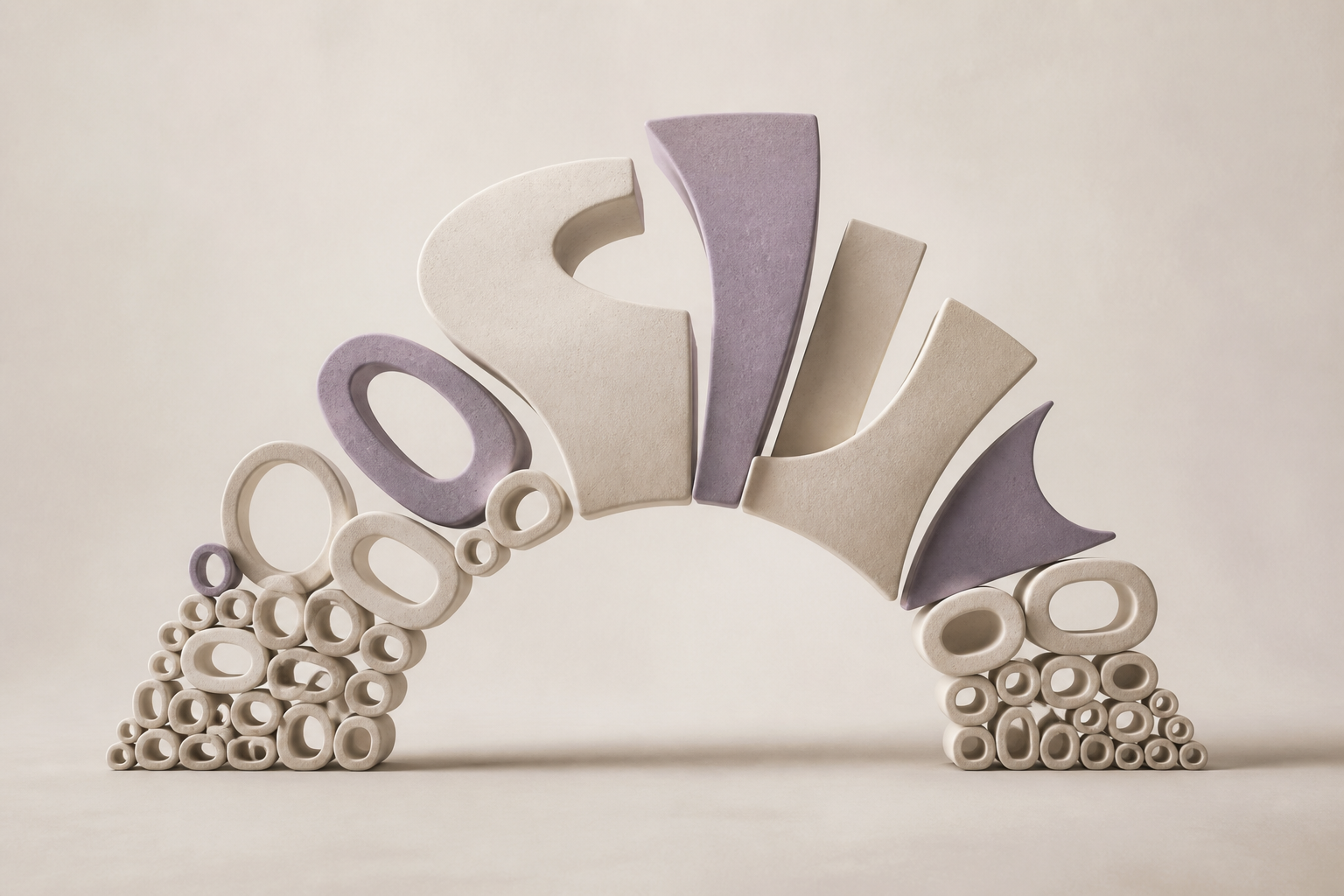
Чем отличаются шрифты без засечек для текста и крупных надписей
Шрифты без засечек для текста и крупных надписей решают разные задачи: первые сохраняют читаемость в длинных строках и при небольшом кегле, вторые создают выразительный образ в заголовке или плакате. Разница заключается в пропорциях, деталях знаков, интервалах и поведении при масштабировании. Ниже разберём, как выбрать подходящий гротеск, настроить набор и избежать ошибок.
Почему один гротеск не одинаково работает везде
Шрифт без засечек, или гротеск, не является универсальным инструментом только потому, что у его букв нет небольших завершающих штрихов. В тексте шрифт должен помогать быстро распознавать слова, удерживать ритм строки и не утомлять взгляд. В крупной надписи он может вести себя смелее: менять ширину знаков, усиливать контраст толщин, использовать необычные формы и заметный характер.
На выбор влияет не только внешний вид букв, но и условия чтения. Статья обычно состоит из множества строк, поэтому важны открытые внутренние просветы, умеренная плотность, различимость похожих знаков и предсказуемые интервалы. Заголовок на обложке читается иначе: у него меньше слов, больше визуального пространства и выше роль силуэта, композиции и эмоционального тона.
Особенности текстового шрифта без засечек
Текстовый гротеск проектируют с расчётом на устойчивое чтение в абзацах, интерфейсах, подписях и навигации. Его буквы обычно имеют хорошо различимые формы, достаточно открытые апертуры и спокойный рисунок. Даже при плотном наборе символы не должны сливаться в серую полосу. Важна и высота строчных знаков: достаточно крупная x-высота помогает сохранить разборчивость, но чрезмерно большая делает текст визуально тяжёлым.
У текстового sans serif часто более нейтральный характер. Это не означает полное отсутствие индивидуальности: различия проявляются в форме кавычек, цифр, знаков препинания, букв а, е, g, в ширине знаков и завершениях штрихов. Однако такие особенности подчинены общей задаче — не отвлекать внимание от содержания. Поэтому хороший текстовый шрифт может казаться незаметным, хотя именно эта незаметность поддерживает комфорт чтения.
На какие признаки смотреть в текстовом гротеске
- Проверяйте различимость похожих букв, например и, й, п, т, ш и щ в кириллице.
- Оценивайте размер внутренних просветов в буквах о, е, с, в и а.
- Смотрите, не становятся ли круглые знаки слишком тесными в длинной строке.
- Проверяйте цифры, скобки, кавычки, тире и другие знаки, а не только алфавит.
- Учитывайте наличие кириллицы, нужных языков, валютных символов и математических знаков.
- Тестируйте обычное, полужирное и курсивное начертания в одном документе.
Что такое дисплейный шрифт для крупных надписей
Дисплейный шрифт предназначен для крупного размера, когда зритель сначала воспринимает общую форму слова, а затем читает отдельные знаки. Он может быть узким, широким, геометричным, мягким, угловатым или контрастным. В заголовке допустимы детали, которые в маленьком кегле исчезли бы или ухудшили бы чтение: необычные терминалы, декоративные соединения, нестандартные пропорции и более заметный ритм.
У дисплейного sans serif сильнее выражен голос бренда или проекта. Крупная надпись на постере должна не только сообщать слова, но и задавать настроение. Геометрический гротеск может выглядеть технологично и строго, гуманистический — дружелюбно, узкий — динамично и экономно расходовать ширину, а тяжёлое начертание — создавать ощущение силы. Эти характеристики работают именно благодаря масштабу и свободному пространству вокруг текста.
Что меняется при увеличении кегля
При крупном размере становятся заметны неровные боковые поля, слишком острые углы, неодинаковая толщина штрихов и неудачная форма отдельных знаков. Поэтому дисплейный набор часто требует ручной настройки кернинга и трекинга. Важен и силуэт строки: одно слово может выглядеть гармонично, а длинная фраза — распадаться на неравномерные пятна. Проверяйте не только отдельные буквы, но и реальный заголовок целиком.
Главные различия текстовых и дисплейных гротесков
- Назначение: текстовый шрифт обслуживает длительное чтение, дисплейный формирует визуальный акцент.
- Пропорции: текстовые гарнитуры чаще рассчитаны на ровный поток слов, дисплейные могут быть экстремально узкими или широкими.
- Детализация: в текстовом варианте детали сдержаны, в крупном начертании допустимы выразительные формы.
- Интервалы: текстовый ритм должен быть стабильным, дисплейный набор чаще требует индивидуальной коррекции.
- Характер: текстовый гротеск обычно нейтрален, дисплейный сильнее влияет на настроение композиции.
- Масштабирование: текстовая гарнитура должна сохранять разборчивость в разных размерах, дисплейная раскрывается прежде всего в крупном кегле.
Как выбрать шрифт под конкретную задачу
Начинайте не с поиска самого красивого шрифта, а с определения роли текста. Если пользователь должен прочитать несколько абзацев, приоритетом становятся удобство, нейтральность и поддержка нужных языков. Если текст состоит из двух или трёх слов на обложке, можно выбирать более характерный дисплейный вариант. Для визуальной системы обычно используют пару: спокойный шрифт для основного текста и акцентный — для заголовков.
Вывод: выбирайте роль, а не только внешний вид
Текстовый гротеск строится вокруг длительного чтения, стабильного ритма и ясности, а дисплейный шрифт — вокруг масштаба, характера и визуального акцента. Лучший выбор определяется задачей, языком, размером, длиной текста и способом публикации. Если вы хотите разработать собственную гарнитуру или выразительный шрифт для крупного заголовка, создайте его на fontgenerator.ru и проверьте в реальном макете.